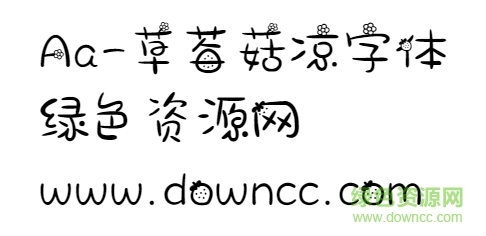
Aa草莓菇?jīng)鲎煮w是網(wǎng)友在草莓妹妹字體上修改來的字體管家系列字體,有著可愛的草莓形狀和 小碎花點(diǎn)綴,讓文字變得更加生動活潑起來,歡迎大家來綠色資源網(wǎng)免費(fèi)體驗哦!
Aa草莓菇?jīng)鲎煮w文字活潑生動,草莓形狀的裝飾讓字里行間充斥著初戀的美好氣息,小編還未大家?guī)硎謾C(jī)版和安裝教程,快來形下載試試吧!